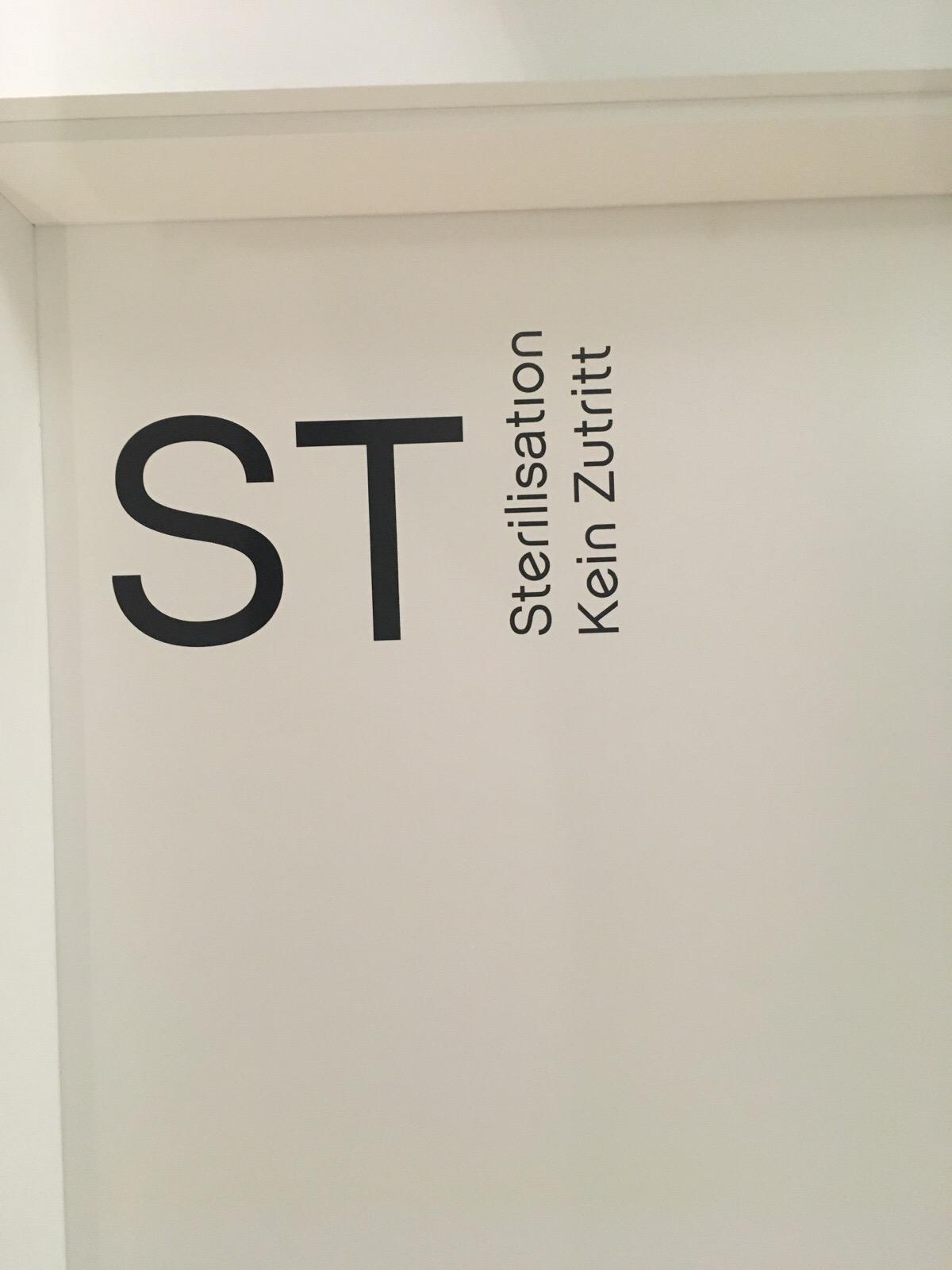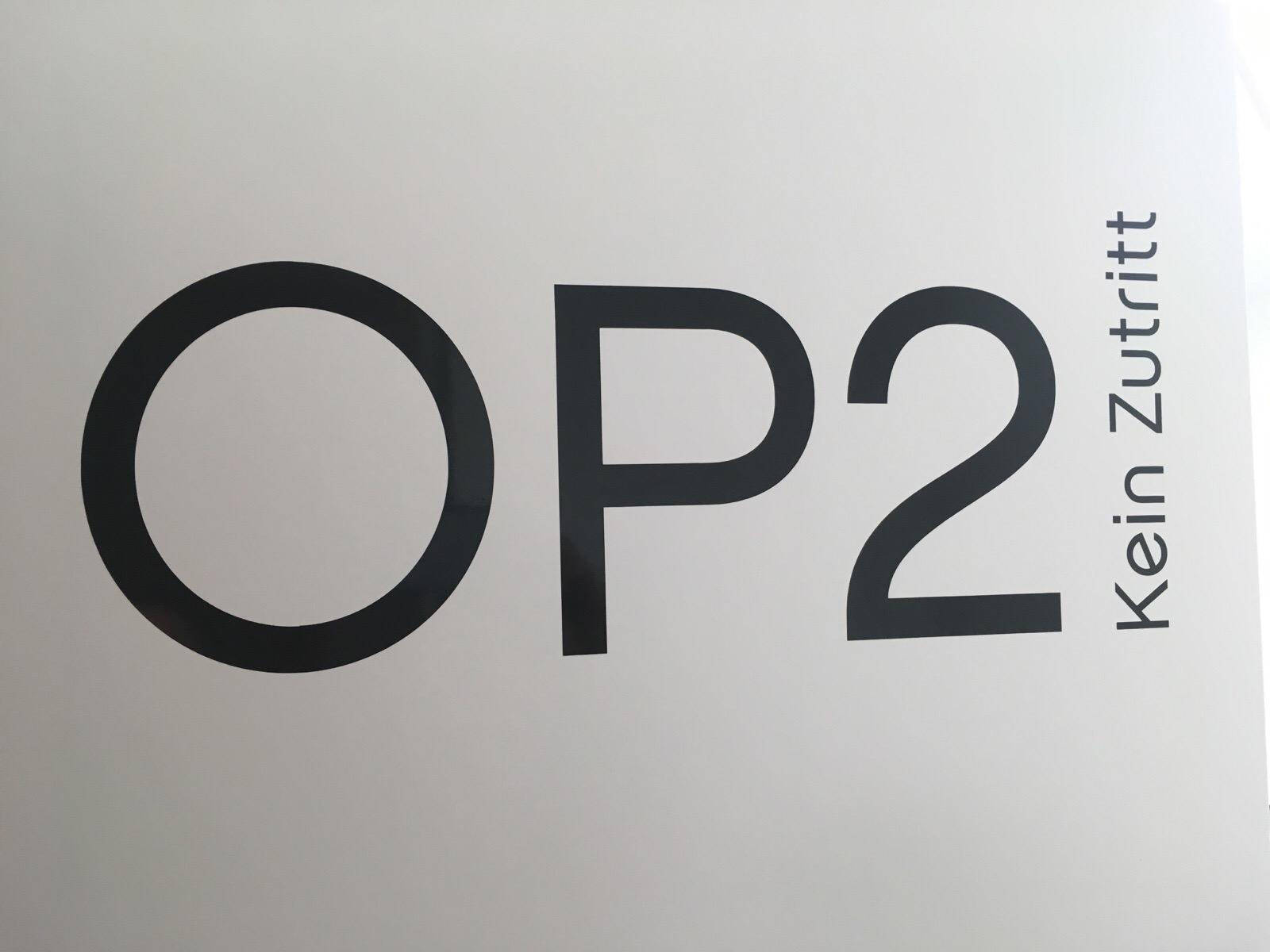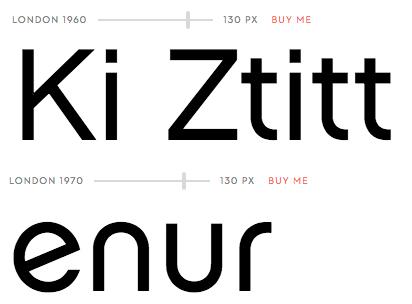
Geometrische Schrift ohne Sporne gesucht
ich bin auf der Suche nach der gezeigten Schrift, leider habe ich keine weiteren Informationen als die Bilder. Auffällig ist das schräge e und die fehlenden Sporne an r und n. Alle üblichen font Identifier habe ich schon durch.
Danke für die schnelle Antwort. Die Chalet London 1970 ist sehr ähnlich die Form des K und der Querbalken beim t weichen jedoch ab.
könnte es sein, dass die Beschriftung aus einer Zeit stammt, in der die Folienplotter mit ner Handvoll Schriften ab Werk kamen? Also irgendwas proprietäres, das es gar nicht digital gibt …?
Ich denke dennoch, das es die Chalet ist. Irgendwo auf der alten Seite von House Ind. habe ich mal gelesen, dass sich die jeweiligen passenden Schnitte (z. B. London 1960, 1970 und 1980) als Alternativbuchstaben (oder auch als Formatsets…?) ganz einfach mischen lassen. Wenn man die passenden Buchstaben aus London 1960 und 1970 ansieht, passt’s m.E.
Ich glaub nicht. Der marginale Unterschied (ist da einer?) kommt u.U. von der schrägen Ansicht …
UPDATE: Ok, wenn ich’s jetzt so untereinander stehen hab, denke ich, du hast doch recht … ;)